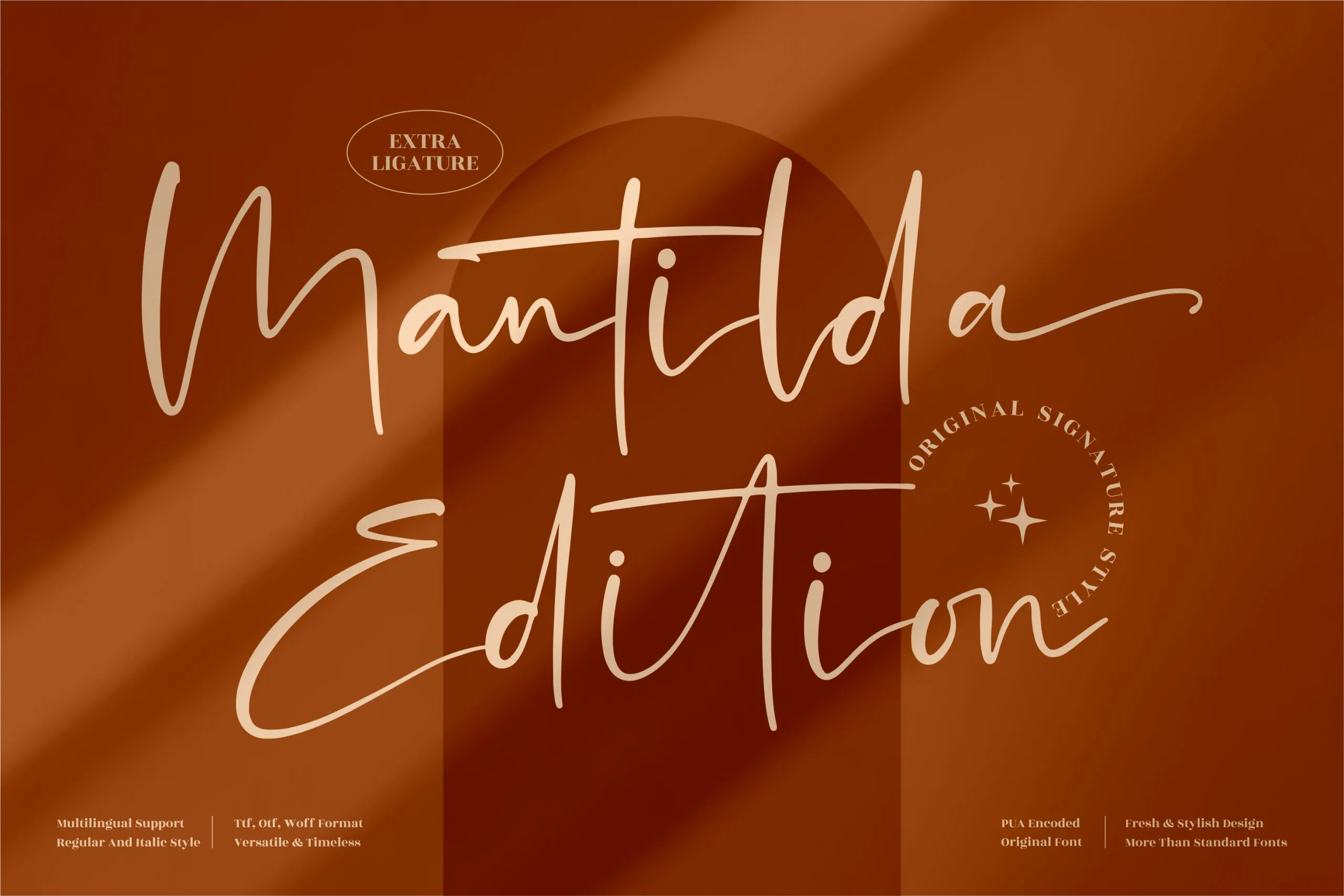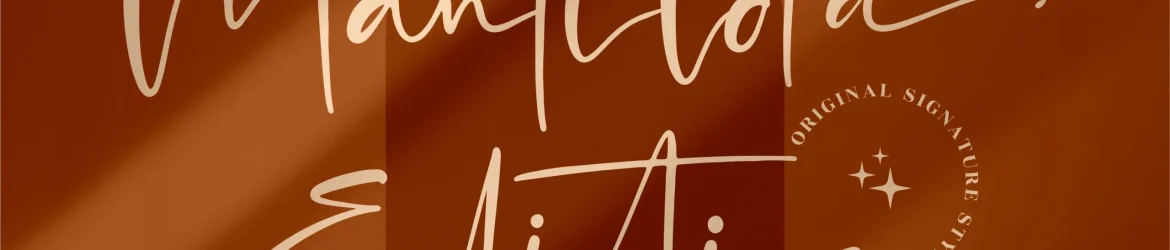
A Mantilda Edition Font é uma elegante escolha para projetos que exigem um toque personalizado, seja ele em logotipos, embalagens ou até mesmo adesivos e revistas de visita. Suas formas delicadas e detalhes sutis fazem dela uma ótima opção para a criação de identidades visuais premium, garantindo que seu projeto atinja um alto nível de qualidade e sofisticação. Além disso, com sua design original e arredondado grãos, ela é perfeita tanto para projetos simples quanto para aqueles mais elaborados e complexos. Suas linhas fluidas são uma excelente escolha para designers que desejam criar um design autêntico e pessoal sem comprometer a qualidade profissional necessária em projetos de alta estima. Com sua tipografia handwritten, Mantilda Edition também é uma fonte perfeita para criações de artesanato. Seja criando tags personalizadas ou adesivos para suas próprias coisas, ela oferece um toque único e autêntico que certamente encantará seu público-alvo. Não importa qual projeto você está trabalhando, a Mantilda Edition tem o poder de criar uma conexão emocional com seus espectadores ao transmitir elegância e confiança. Portanto, para todos aqueles projetos em que precisam de um toque personalizado, esta fonte é uma excelente opção premium para dar seu projeto aquela última cheirada de qualidade.